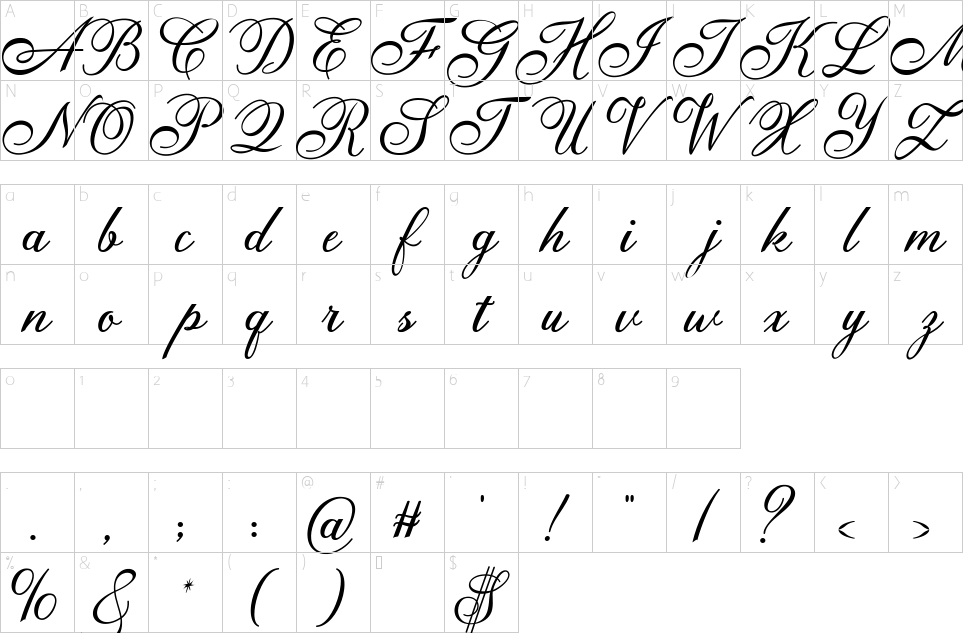
Anatomia é uma fonte originalmente criada pelo designer de arte digital, Doel Creative. Esta fonte tem sido uma escolha popular para designers de todo o mundo, especialmente para projetos que precisam de um equilíbrio harmônico entre clareza e elegância. Com seus traços finos e leves, a Anatomia é perfeita para trabalhos de texto e títulos, oferecendo uma aparição suave e sofisticada. A fonte foi baixada 36,602 vezes, demonstrando sua popularidade e qualidade. Se você está procurando uma fonte moderna, elegante e versátil para seus projetos digitais, Anatomia pode ser a escolha perfeita para você.